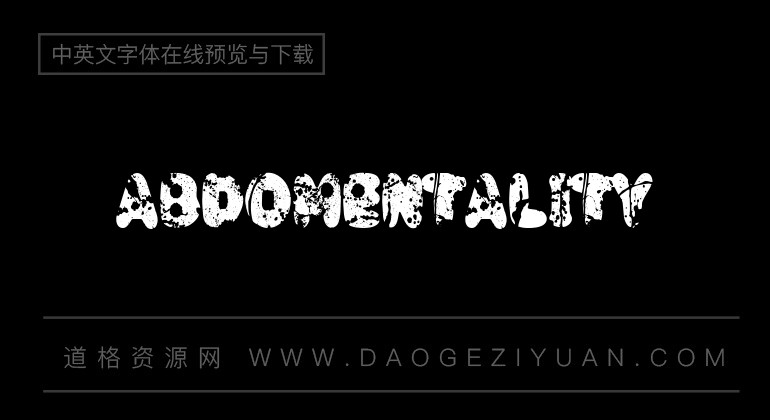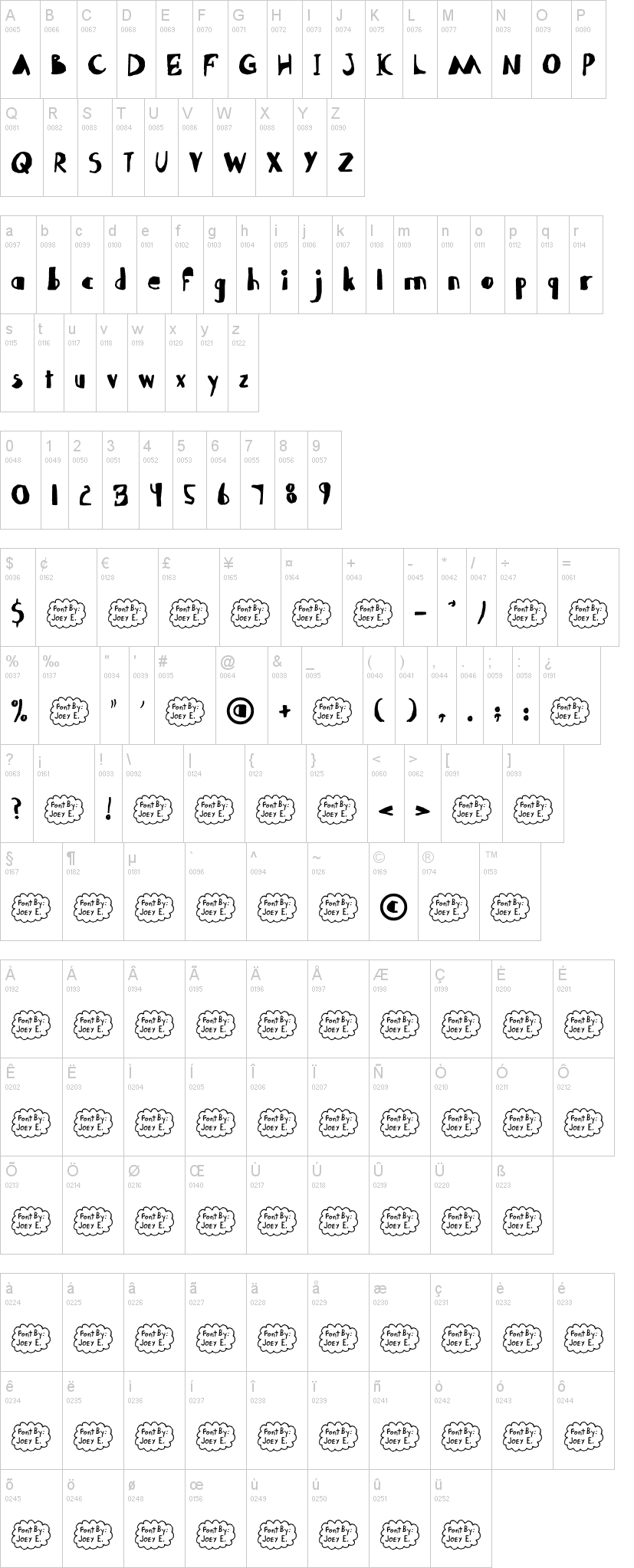
Abdomentality
? Abdomentality 是一款由荷兰设计师 Martin Majoor 开发的字体,它是一种抽象的、灵活的字体,具有良好的可读性和可访问性。它的特点是有较大的空间,可以在空间有限的情况下显示更多的文本,并且可以在屏幕上清晰地显示出来。此外,它还具有良好的可扩展性,可以根据需要进行调整,以适应不同的尺寸和环境。
Abdomentality是一款非常不错的手写艺术字体,具有很好的视觉感,适合于文化类的宣传设计、商业类品牌的广告和产品包装设计以及个性化文字排版等较多场景。
Abdomentality字符映射图